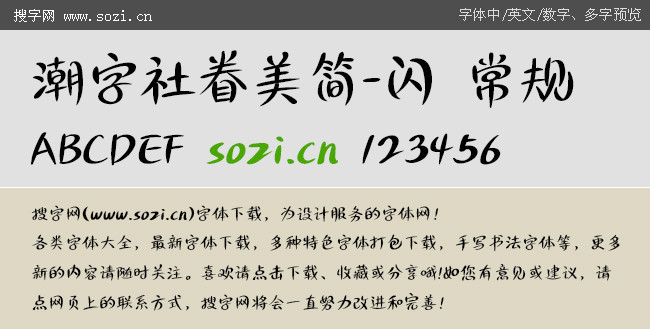
潮字社眷美簡-閃 常規
搜字網提供一款潮字社眷美簡-閃 常規中文字體下載,潮字社眷美體是一款線條優美圓潤的藝術字體,風格比一般的字體更有特色,連貫字跡顯得干練而不凌亂,清新簡明,具有很好的視覺感,適合應用于藝術設計、平面宣傳設計、網頁設計等領域等應用。(本字體為個人非商用版,商用請聯系作者購買授權)